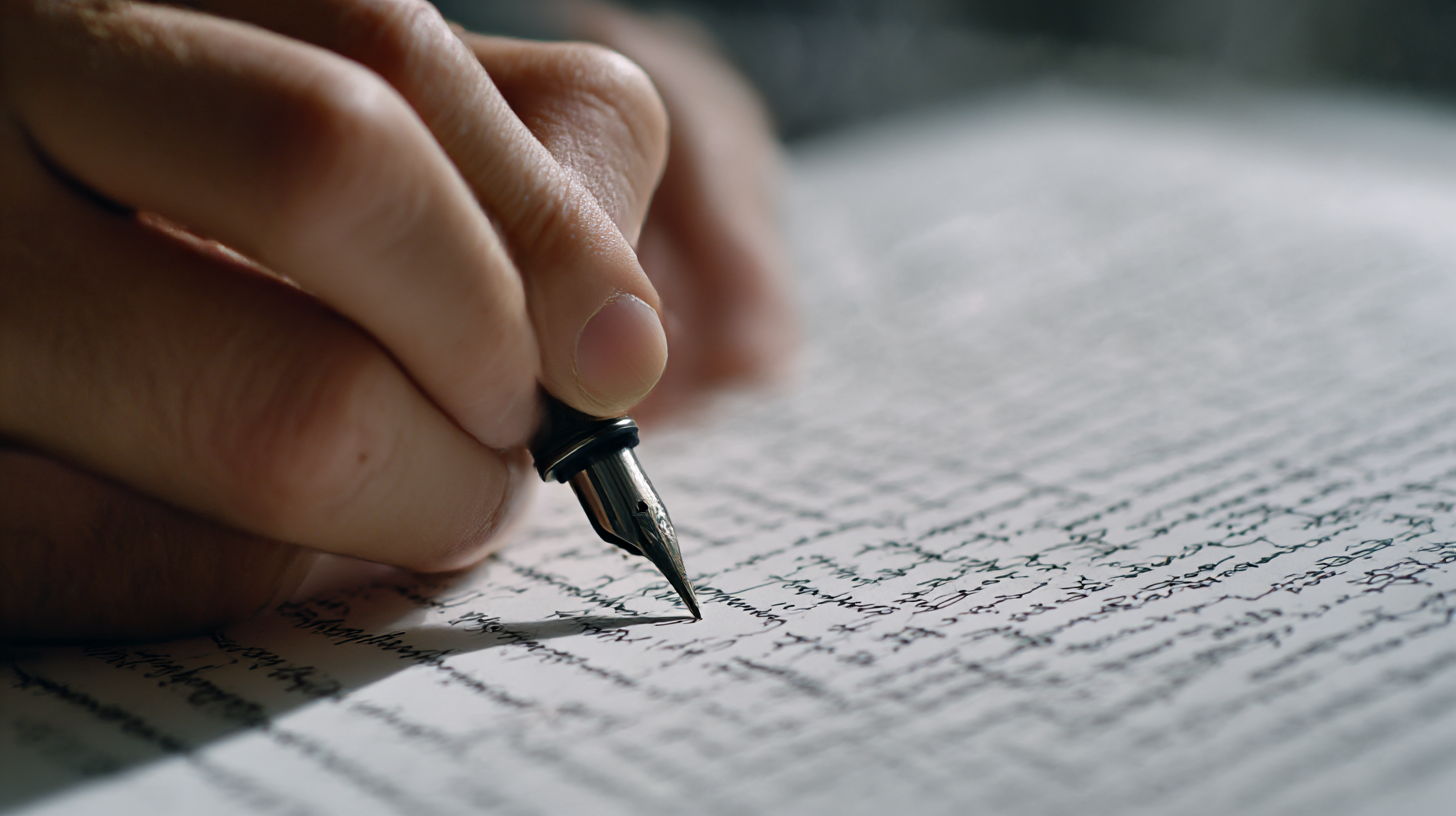
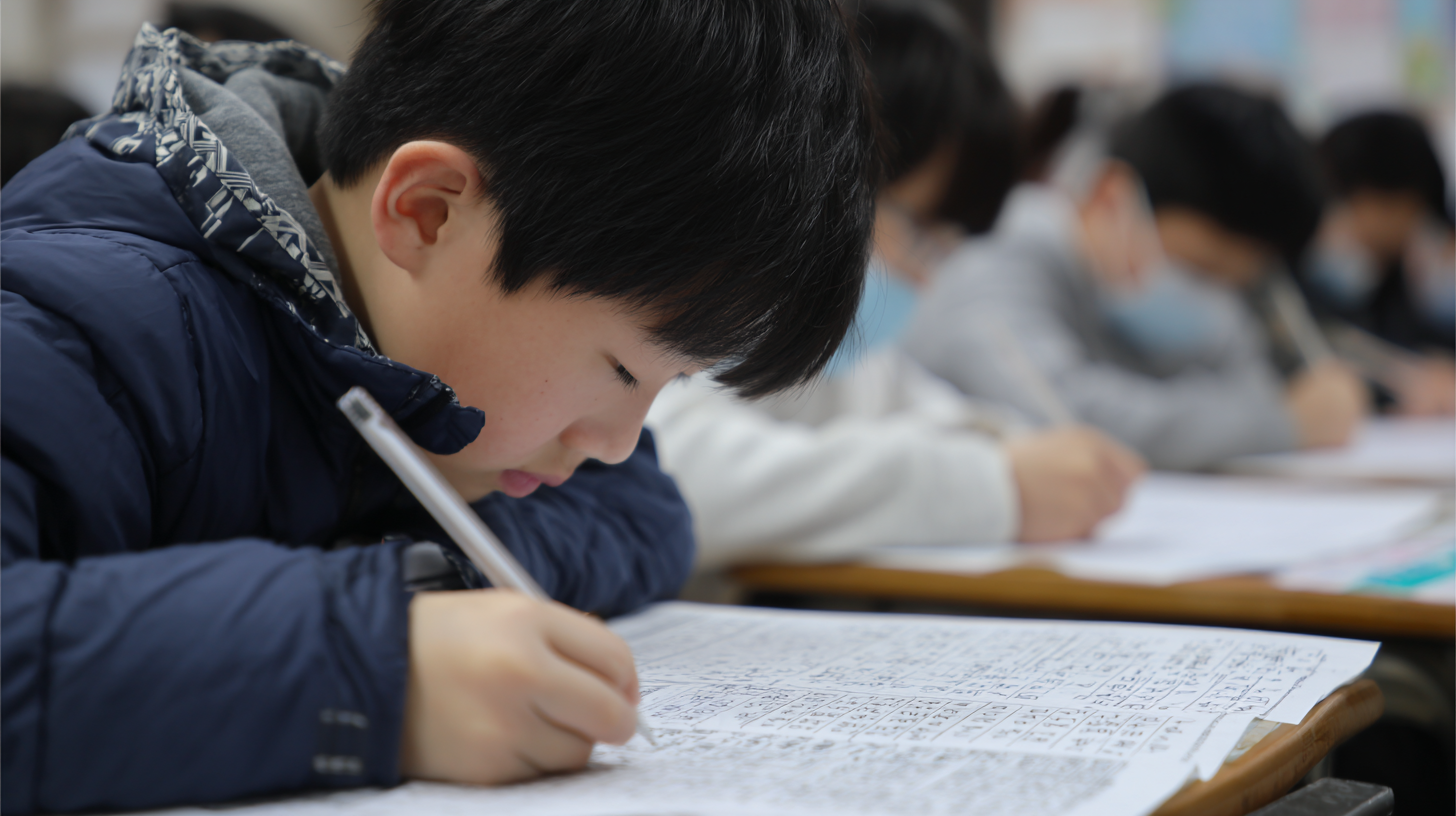
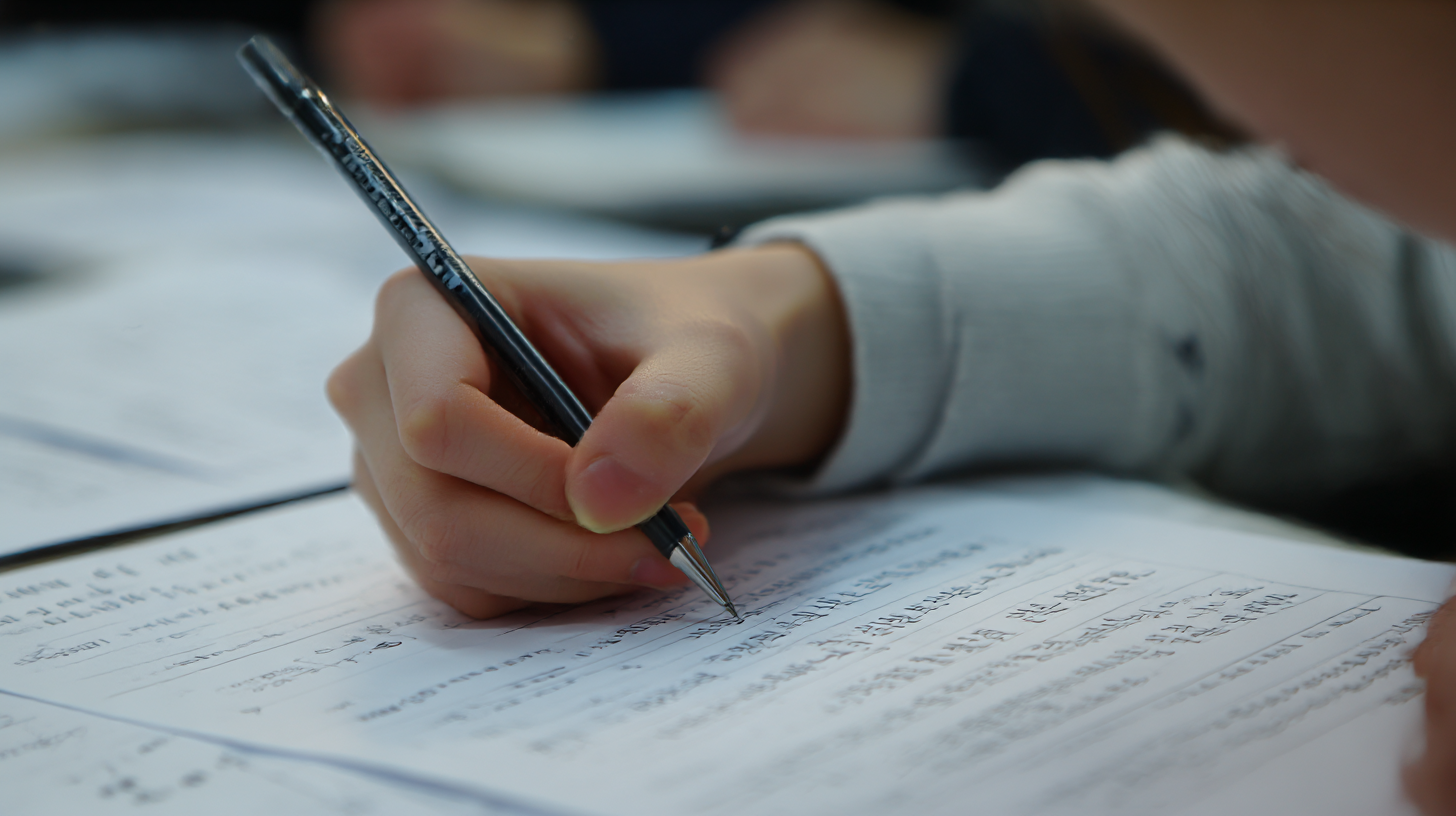
예쁜 글씨를 쓰려면 꼭 해야 할 연습법 3가지 예쁜 글씨를 쓰고 싶다면 무작정 따라 쓰는 것만으로는 부족해요. ✍ 글씨 교정은 올바른 연습법을 익히는 것이 중요하죠. 오늘은 예쁜 글씨를 만들기 위해 꼭 실천해야 할 연습법 3가지를 알려드릴게요! 🖋
이 방법들을 꾸준히 연습하면 손글씨가 훨씬 깔끔하고 예뻐질 거예요. 자, 그럼 첫 번째 연습법부터 시작해볼까요? 🚀
✍ 연습법 1: 기본 선 연습하기
예쁜 글씨의 기본은 선을 정확하게 그릴 수 있는 능력에서 시작돼요. 마치 그림을 그릴 때 선 연습을 하듯, 글씨도 기본 선 연습이 매우 중요하답니다! 🖋
많은 사람들이 글씨를 교정할 때 단어나 문장을 따라 쓰는 연습부터 시작하는데, 사실 그 전에 선 연습부터 해야 손의 힘 조절과 필기 감각이 좋아져요. 📏
기본 선 연습은 가로선, 세로선, 곡선 등을 일정한 간격으로 반복해서 그리는 방식으로 진행돼요. 이런 연습을 하면 글씨의 균형이 맞아지고, 선의 떨림도 줄어들죠. 🎯
📏 기본 선 연습법 종류
연습법 설명 효과 가로선 연습 수평선을 일정한 간격으로 긋기 균형 잡힌 글씨 쓰기 연습 세로선 연습 수직선을 일정한 길이로 긋기 글씨의 일정한 크기 유지 곡선 연습 부드러운 곡선을 일정한 간격으로 그리기 손의 유연성과 글씨의 흐름 개선 이렇게 기본 선을 연습하면 글씨를 쓸 때 자연스럽게 선이 고르게 나오고, 글씨가 한 방향으로 기울어지는 문제도 줄어들어요. 😊
그럼 이제 글씨의 균형을 맞추는 두 번째 연습법을 알아볼까요? 🎯
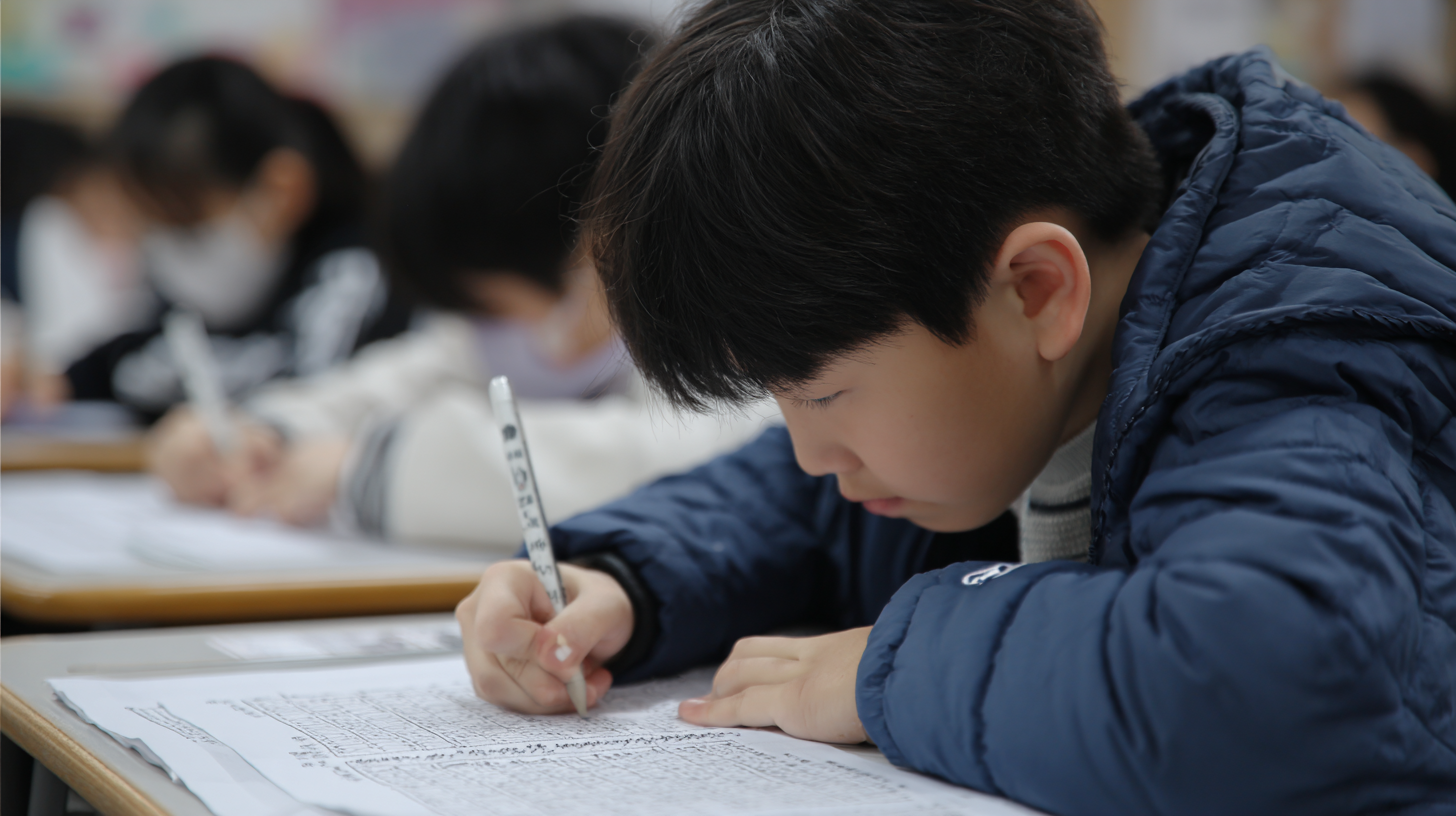
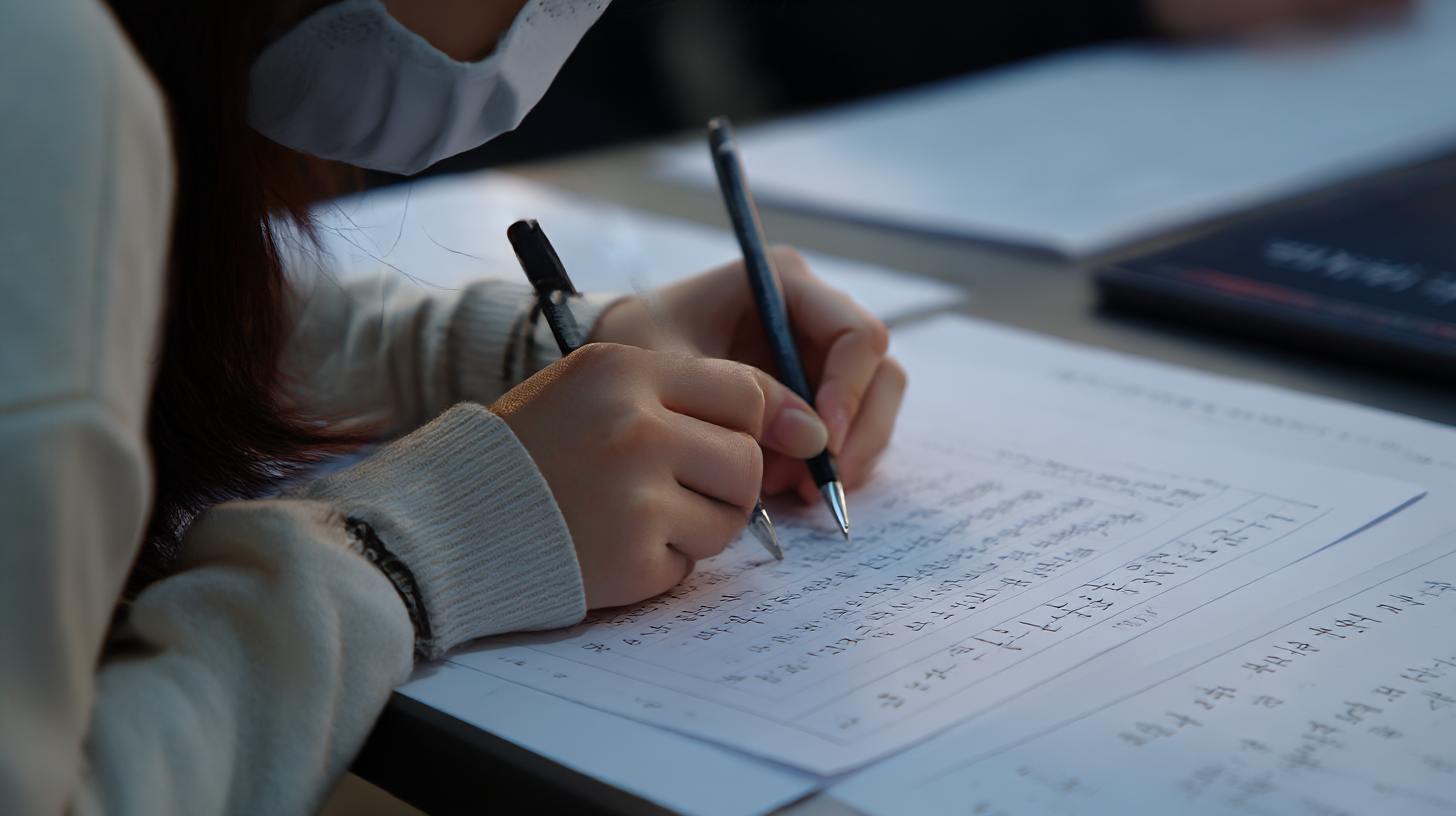
기본 선 연습하기 ⚖ 연습법 2: 글씨의 균형 맞추기
예쁜 글씨는 균형이 잘 맞아야 해요. 글자가 한쪽으로 기울어지거나 크기가 들쑥날쑥하면 깔끔한 인상을 줄 수 없어요. ✍
글씨의 균형을 맞추는 연습을 하면 모든 글자가 일정한 크기와 간격을 유지할 수 있어요. 그러면 읽기 편하고, 보기에도 훨씬 깔끔한 손글씨가 완성되죠! 🎯
이 연습에서는 '모눈 종이' 또는 '글씨 교정 노트'를 사용하면 좋아요. 한 줄의 높이를 일정하게 맞추고, 글자의 간격도 균등하게 조절하는 것이 핵심이랍니다! 📏
📐 글씨 균형 맞추기 연습법
연습법 방법 효과 모눈 종이에 연습 모눈 종이에 글자를 써서 크기와 간격을 맞추기 글자 크기와 배치 균형 잡기 줄 맞춰 쓰기 가이드라인을 사용해 글씨의 높이를 일정하게 유지 글씨의 정렬이 깔끔해짐 간격 조절 연습 글자와 글자 사이의 간격을 일정하게 조절 읽기 쉬운 글씨 완성 이 연습을 꾸준히 하면 글씨가 한쪽으로 기울어지거나, 크기가 불규칙한 문제를 해결할 수 있어요! 😊
그럼 이제 마지막 연습법, '필기 속도 조절하기'를 알아볼까요? 🚀
🐢 연습법 3: 필기 속도 조절하기
글씨를 예쁘게 쓰기 위해서는 속도를 조절하는 것이 매우 중요해요. 너무 빠르게 쓰면 글자가 흐트러지고, 너무 느리면 자연스러운 필기체가 나오지 않아요. 적절한 속도로 글씨를 쓰는 것이 균형 잡힌 글씨체를 만드는 핵심이에요! ⏳
많은 사람들이 글씨를 연습할 때 최대한 빨리 따라 쓰려고 하지만, 처음에는 속도를 줄이고 한 글자 한 글자 정확하게 쓰는 것이 중요해요. 손과 필기구의 움직임을 조절하며 필기 속도를 맞추는 연습을 하면 더 깔끔한 글씨를 쓸 수 있답니다. 🖋
필기 속도 조절 연습은 두 가지 방식으로 진행하면 효과적이에요: 처음에는 천천히 써서 정확도를 높이고, 이후 점점 속도를 올려 자연스러운 흐름을 만드는 거예요. 🚀
⏳ 필기 속도 조절 연습법
연습법 방법 효과 천천히 따라 쓰기 처음에는 아주 느리게 글자를 써서 정확도를 높임 획의 방향과 균형 감각 향상 점진적 속도 증가 조금씩 속도를 높이며 자연스러운 필기 연습 부드럽고 흐름 있는 글씨체 형성 리듬감 유지 박자감을 맞춰 일정한 속도로 글씨를 써보기 일관성 있는 글씨체 완성 이 연습을 꾸준히 하면 글씨가 지나치게 빠르거나 느려지는 문제를 해결할 수 있어요. 자연스럽고 보기 좋은 필기체를 만들 수 있답니다! 😊
이제 예쁜 글씨를 위한 3가지 필수 연습법을 모두 알아봤어요! 그럼 사람들이 자주 궁금해하는 글씨 교정 관련 질문을 FAQ에서 확인해볼까요? 🔍
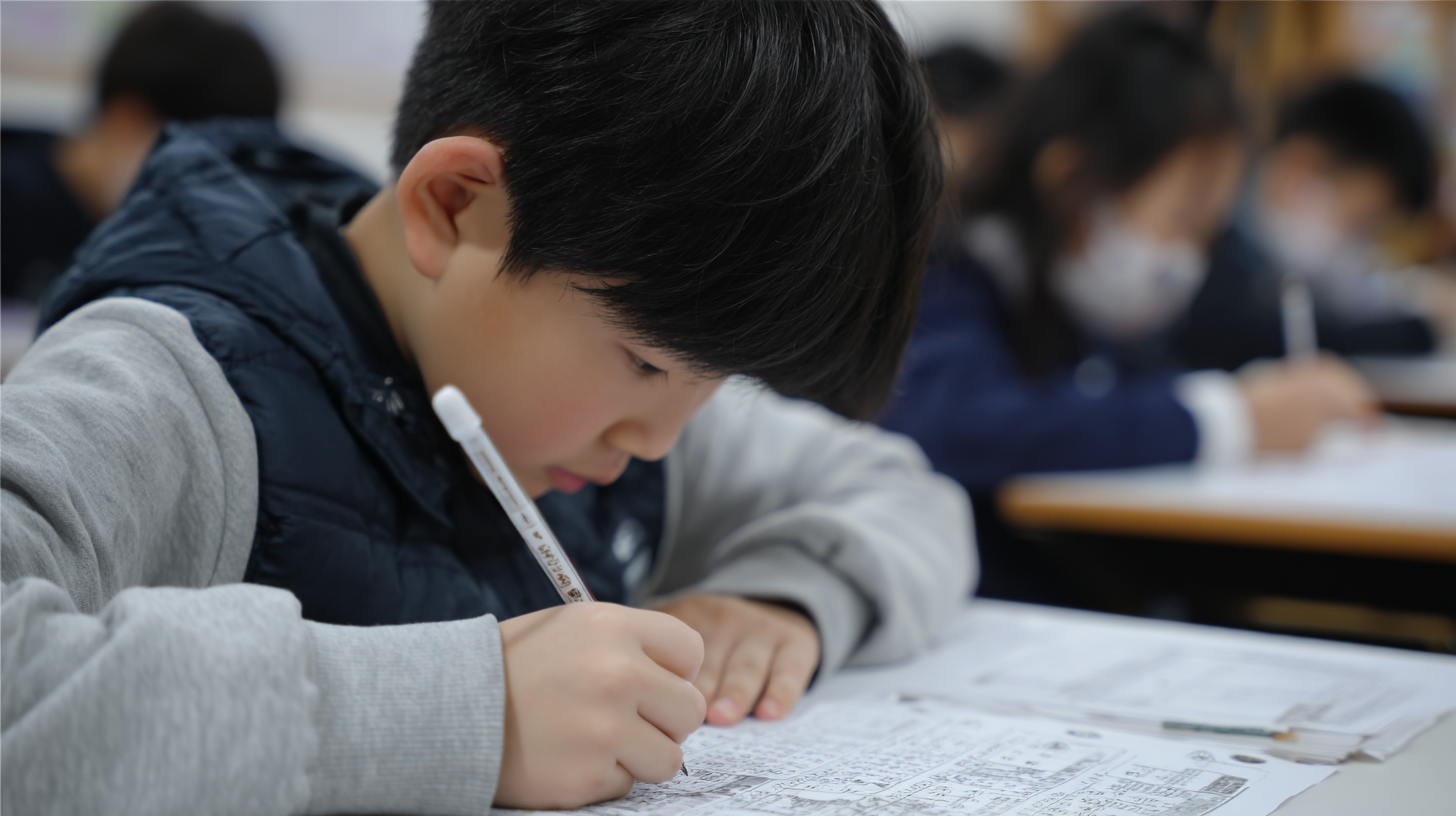
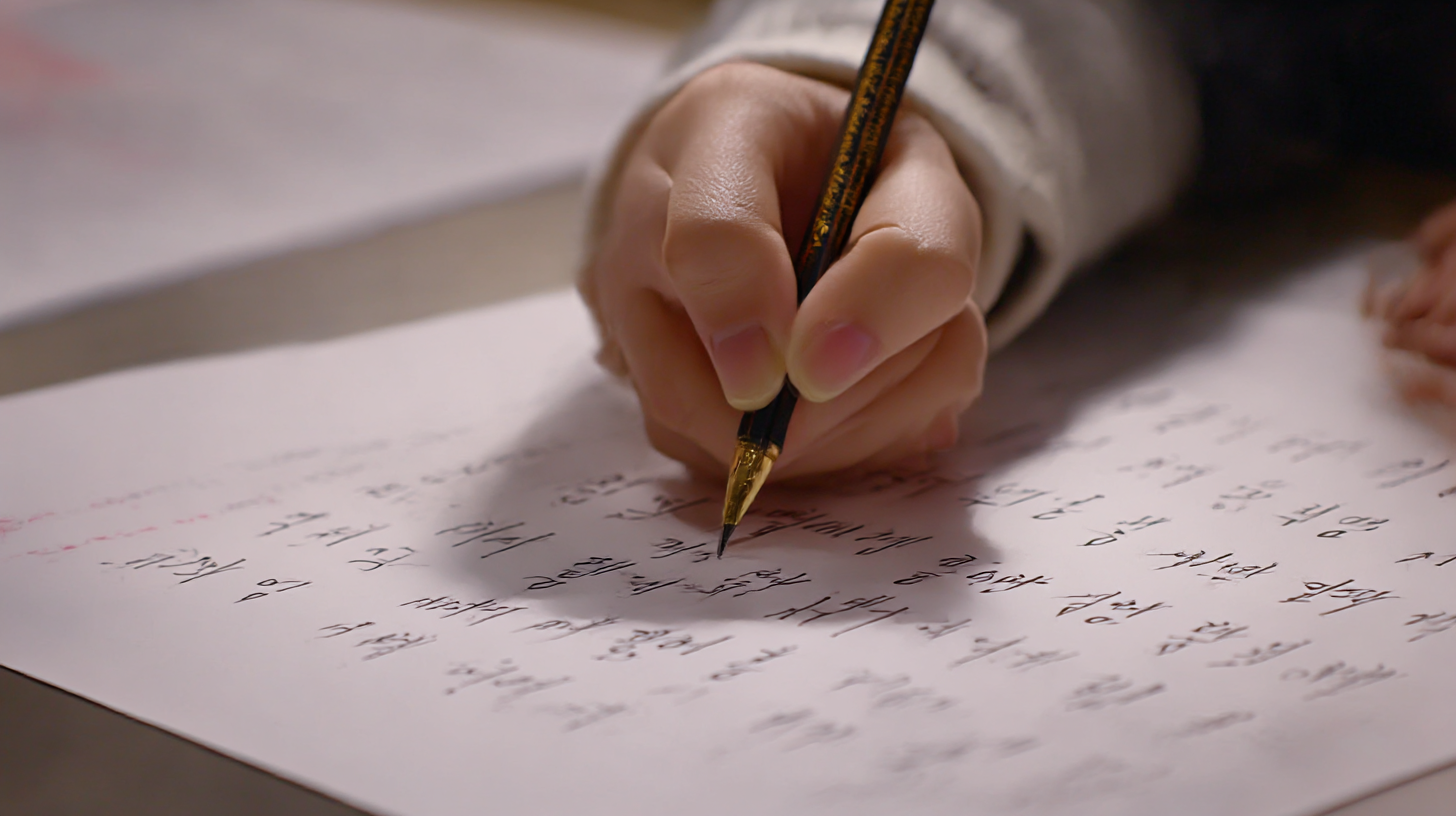
필기 속도 조절하기 ❓ FAQ
Q1. 글씨 교정은 하루 몇 분씩 연습해야 효과가 있나요?
A1. 하루 15~30분 정도 꾸준히 연습하는 것이 가장 효과적이에요. 짧은 시간이라도 매일 연습하면 손의 근육이 적응하면서 글씨체가 자연스럽게 교정된답니다. ✍
Q2. 글씨 연습할 때 연필과 펜 중 어떤 게 더 좋은가요?
A2. 초보자는 연필이 좋아요! ✏ 연필은 미끄러지지 않고 필압을 조절하기 쉬워서 글씨 교정에 유리해요. 그러나 실제 필기 환경에서는 펜을 많이 사용하므로, 연습이 익숙해지면 볼펜이나 만년필로도 연습해보세요.
Q3. 글씨를 더 빨리 교정할 수 있는 비법이 있나요?
A3. 네! 📏 1) 기본 선 연습을 충분히 하고, 2) 균형 잡힌 글씨를 쓰는 연습을 하며, 3) 필기 속도를 조절하면 훨씬 더 빠르게 교정할 수 있어요! 😊
Q4. 글씨 교정을 위한 추천 연습장은 무엇인가요?
A4. 모눈종이나 가이드라인이 있는 연습장이 좋아요. 📖 특히 ‘한 줄 필사 노트’나 ‘글씨 교정 워크북’을 활용하면 더욱 효과적이에요!
Q5. 악필이 심한 사람도 글씨를 교정할 수 있나요?
A5. 물론이죠! 💪 악필도 꾸준한 연습을 통해 충분히 교정할 수 있어요. 특히 ‘기본 선 연습 + 필기 속도 조절’을 병행하면 빠르게 개선된답니다.
Q6. 글씨 연습을 하면 손이 아픈데, 어떻게 해야 하나요?
A6. 손에 힘을 너무 많이 주지 마세요! ✋ 필기 전 손 스트레칭을 해주고, 필기구를 가볍게 잡는 습관을 들이면 손의 피로를 줄일 수 있어요.
Q7. 글씨 연습을 할 때 음악을 들으면 도움이 되나요?
A7. 네, 클래식 음악이나 잔잔한 연주곡을 들으면 집중력을 높이는 데 도움이 돼요. 🎵 너무 빠른 템포의 음악보다는 차분한 음악이 글씨 연습에 적합하답니다!
Q8. 하루 만에 글씨체가 달라질 수 있나요?
A8. 하루 만에 완벽한 변화는 어렵지만, 기본 선 연습과 속도 조절을 병행하면 눈에 띄는 개선 효과를 볼 수 있어요. 꾸준히 연습하면 확실한 변화를 느낄 수 있답니다! 🚀
예쁜 글씨를 만들기 위한 필수 연습법 3가지를 모두 알아봤어요! 이제 꾸준히 연습해서 손글씨를 더 아름답게 만들어보세요! ✨